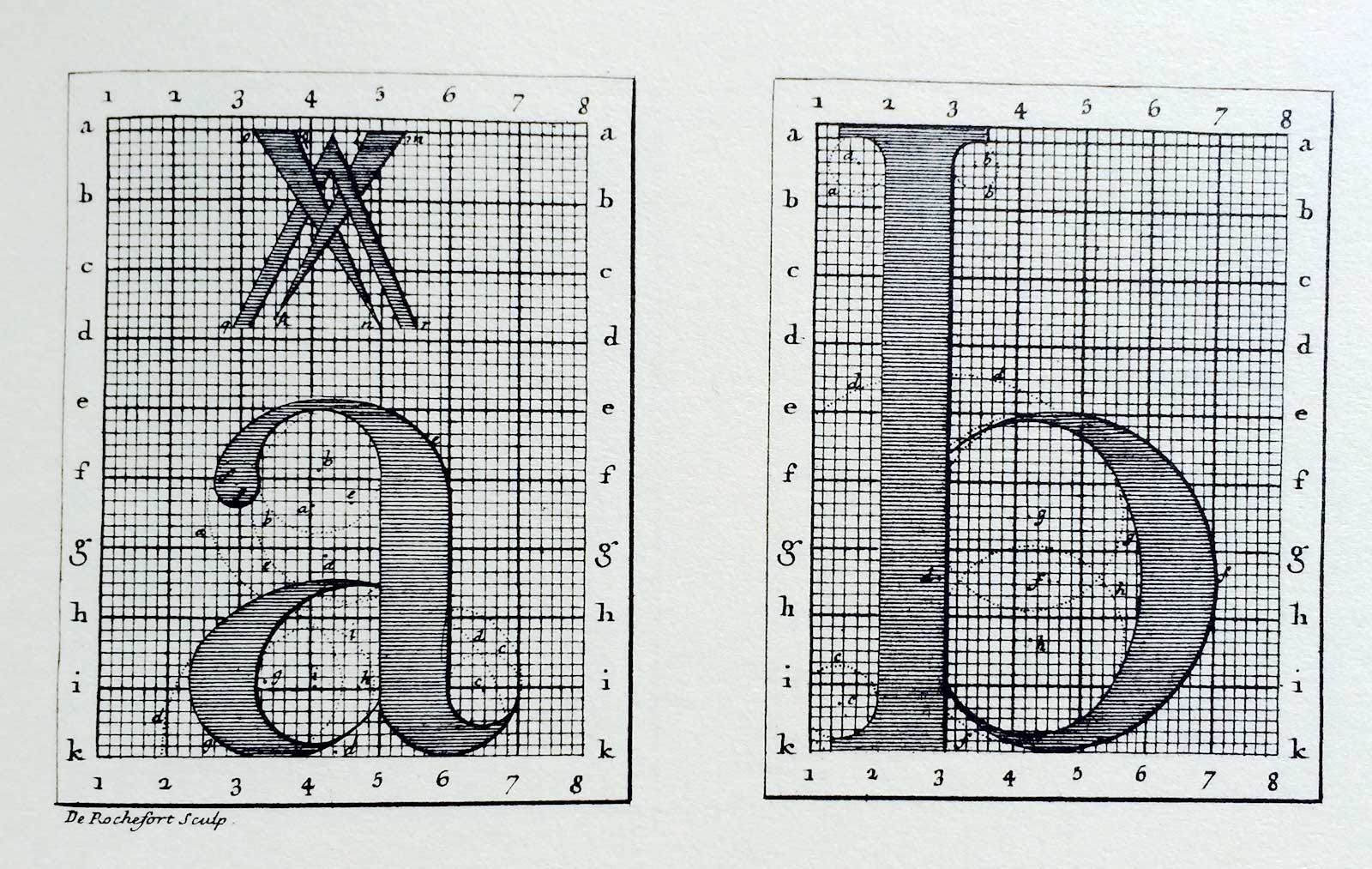
Em meados de 1640, havia na Europa dois tipos de pessoas que acreditavam em demônios: cristãos em geral e René Descartes. Não que o filósofo francês acreditasse mesmo na ideia de inferno e quaisquer de seus supostos habitantes; seu demônio parecia um fantasma ou assombração. Um “demônio maldoso de grande poder e astúcia (que) tenha empregado suas energias para me enganar”, dizia ele em suas meditações, mas sem creditar qualquer existência de facto à criatura. Seu demônio maldoso era um exercício de pensamento para suspender toda crença oriunda de fontes não-confiáveis — entre elas, os sentidos —, criando uma metodologia racional para a investigação da verdade sobre as coisas, o que tratamos como pensamento cartesiano.
Descartes alinha-se entre outros pensadores do séc. XVII, como Francis Bacon e John Locke, no período conhecido como Revolução Científica, em que a ciência é dissociada da teologia, e o método científico sobrepõe-se ao senso comum e empirismo como forma de validar o conhecimento. Esse período é importante para o movimento Iluminista, que levou o domínio da razão para outras áreas, como a política, direito e as artes no século seguinte, culminando na Revolução Francesa de 1789. Uma amostra do quanto essa mudança de mentalidade foi profunda na sociedade europeia é o tema de hoje, que conhecemos como o primeiro projeto encomendado de design de tipos da história da tipografia: a Romain du Roi (pode chamar de Ruman Durruá, ou apenas de Romanas do Rei).
Antes de falar do projeto em si, é importante esclarecer porque tratamos as Romanas do Rei como um projeto pioneiro de type design no mundo. Já falei em outra edição sobre o momento histórico em que as letras romanas foram concebidas e tomaram o lugar dos tipos blackletter gravados por Gutenberg. Essas letras romanas, gravadas por Speyer, Jenson e outros no séc. XVI, nunca perderam características advindas da caligrafia humanista italiana, como o eixo inclinado das letras redondas e os contrastes e terminações feitas com bico de pena.
Abrir letras era um ofício passado para poucos aprendizes, baseado na experiência dos abridores (punchcutters) e no próprio senso estético do abridor. Uma letra “a” feita por abridores como Garamond, Granjon, Estienne, Griffo e outros refletia a forma ideal que essa letra “a” deveria ter em qualquer contexto. Uma fonte desses abridores não era um projeto com duração determinada, mas sim um trabalho de uma vida inteira. Isso parece romântico para a gente, mas do ponto de vista racional, a ideia de que as formas das letras são como são pela mera expressividade de seus abridores é questionável. Todo atributo de uma fonte deveria ter uma razão fundamentada em algo verificável e independente de crenças. Dessa forma, as letras concebidas sob essa razão não mudariam apenas pela vontade do abridor ou a mera passagem do tempo: a matemática e trigonometria seriam ferramentas para uma descrição universal e atemporal dessas letras.
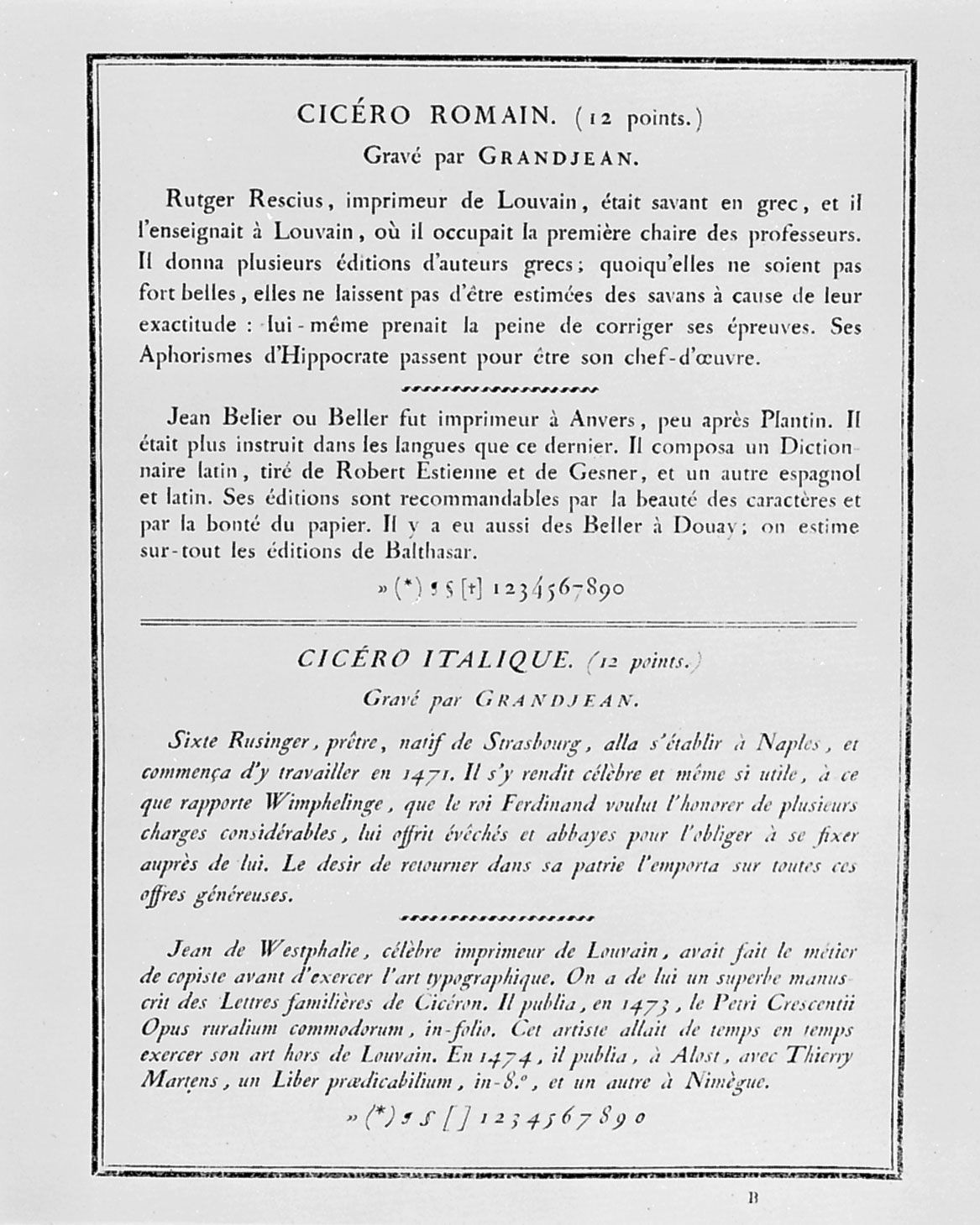
Olhar para as formas das letras com rigor matemático e geométrico era uma ideia semeada quase um século e meio antes das Romain du Roi. O tratado de Albrecht Dürer de 1525, “Do Desenho Das Letras”, traz uma visão geométrica e deveras racional para as formas das letras romanas maiúsculas (vistas na famosa Coluna de Trajano e outros monumentos) e góticas “textura” (também chamadas blackletter). Os esquemas construtivos de Dürer, que empregavam retas com curvas tangentes em pontos bem calculados, representavam o pensamento renascentista de exaltação das ciências como algo divino. Pense no “Homem Vitruviano”, de Leonardo da Vinci, mas com letras, vistas como um projeto de uma engenharia perfeita.
Só que essa racionalidade renascentista buscava “encontrar Deus”, enquanto a mentalidade empregada pela comissão Bignon, designada pelo rei francês Luís XIV (sim, o que era chamado de Rei Sol e supostamente cunhou a expressão símbolo do absolutismo “l’état, c’est moi”) em 1692, buscava consolidar o poder intelectual de sua nação. O monarca nomeou alguns notáveis em ciências, além do tipógrafo Jacques Jaugeon, para a criação de um alfabeto nacional na Academia Francesa de Ciências. Além das Romain du Roi, a comissão liderada pelo abade Jean-Paul Bignon buscava examinar e registrar os processos industriais e práticas de produção artísticos da França Imperial. O fim do século XVII foi uma época desenvolvimentista, marcada por grandes construções, importantes descobertas científicas e o registro desse progresso e de todo o conhecimento da humanidade em enciclopédias.
As romanas foram projetadas por Jaugeon e os matemáticos Sébastien Truchet e Gilles Filleau Des Billets, e gravadas por Louis Simmoneau. As letras desenhadas em grids de 8×15 (minúsculas) e 8×8 (maiúsculas), por sua vez, não tinham uma ambição metafísica de encontrar pi ou uma espiral de Fibonacci. A ideia das Romain du Roi é mais racionalista: documentar as técnicas usadas na prática das artes tipográficas e, por influência de Truchet, propor uma visão geométrica e intelectual para a criação de letras. Havia também um ideal nacionalista de expressar nas formas das letras a grandiosidade da monarquia francesa. Os desenhos originais, finalizados em 1695, mostram letras que começam a abandonar várias características das letras romanas feitas à mão, como o eixo perpendicular à linha de base (ao invés do eixo inclinado, como era comum), o contraste mais acentuado entre traços finos e grossos (acompanhando melhorias na tecnologia de produção de tintas e tipos móveis), serifas retas e terminais que não guardavam mais vestígios de ferramentas de escrita.
Para gravar as letras aprovadas pela comissão Bignon, foi designado o abridor Philippe Grandjean, que precisou de sete anos para que os primeiros tipos do projeto inicial fossem usados. Certa parte dessa demora é creditada às adaptações que as letras sofriam quando gravadas por Grandjean, inspirado pelo trabalho do mestre calígrafo francês Nicolas Jarry, com belas letras abertas quase 50 anos antes. Elas eram necessárias para que funcionassem no dia-a-dia da Imprimerie Royale, mas nem sempre passavam pelo crivo da comissão. É comum, por isso, observar certos caracteres das Romain du Roi que são distantes dos traços ortogonais rigorosos de Simmoneau e ainda mantêm uma leve conexão dessas letras com a tradição caligráfica.
Em 1702, as Romain du Roi foram usadas pela primeira vez no Médailles sur les principaux énvenémens du règne de Louis-le-Grand (Medalhas nos principais eventos do reinado de Luís, o Grande), e foi o único conjunto de fontes usado pela imprensa régia francesa até 1811. No entanto, o trabalho de criar todas as 42 fontes (21 tamanhos, normais e itálicos) da Romain du Roi levou mais 45 anos, ficando prontas apenas em 1745. Grandjean faleceu nesse período, sendo sucedido por seu aprendiz Jean Alexandre e, depois, por Louis Luce. Uma das inovações trazidas pela comissão Bignon foi a adoção de um sistema lógico para nomear cada uma das fontes de acordo com o seu tamanho. Até então, era comum o uso de nomes arbitrários (como Cicero, St. Augustin ou Parisienne) para tamanhos diferentes da mesma família de fontes, e esses nomes mudavam até mesmo entre gráficas. Truchet fez uma análise desses tamanhos entre gráficas e propôs uma unidade de medida fixa para cada tamanho de fonte. Seu sistema ultra-preciso, com o tempo, foi refinado por Pierre Simon Fournier e Firmin Didot.
Os tipos criados pela comissão permaneceram exclusivos à Imprimerie Royale, a gráfica real francesa criada em 1640, mas serviram de inspiração para vários tipógrafos e abridores de letras da Europa, sendo um ponto de transição das letras romanas oldstyle (em que se encaixam os tipos de Jenson, Garamont e Granjon, por exemplo) para o futuro estilo de fontes serifadas modernas, nas quais encaixam-se os tipos de Giambattista Bodoni e Didot. Algumas características desse estilo transicional da Romain du Roi apareceriam mais tarde nos tipos de William Caslon e John Baskerville, muito utilizados atualmente em versões digitais.